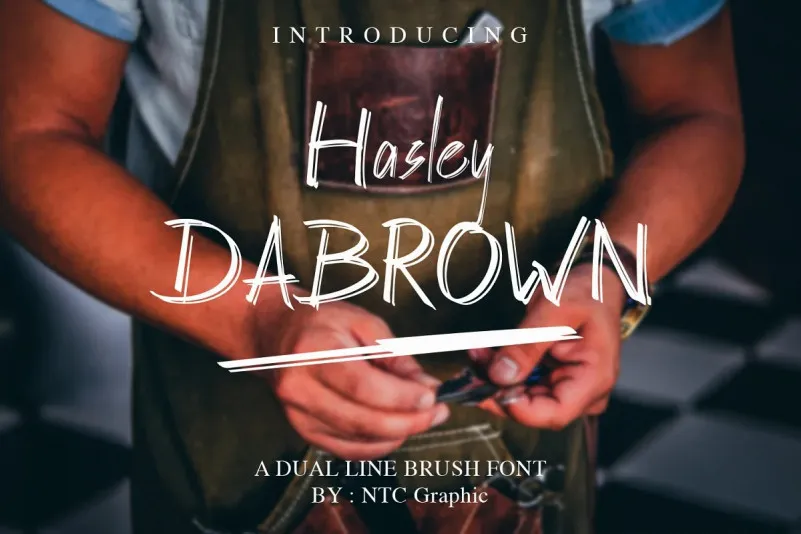
A Hasley Dabrown Font é uma elegante tipografia script desenvolvida pela NTC Graphic, com linhas suaves e textura bem definida. Ideal para designers de t-shirts, cartões de visita artísticos e branding, essa fonte chic e sofisticada também atende às necessidades de flyers e criação gráfica geral. Seu estilo arredondado e harmonioso transmite elegância sem comprometer a modernidade, tornando-a uma escolha perfeita para estilos tanto vintage quanto contemporâneos. Com sua composição detalhada e linhas artísticas, Hasley Dabrown oferece um toque sofisticado que certamente adicionará um charme especial aos seus projetos.